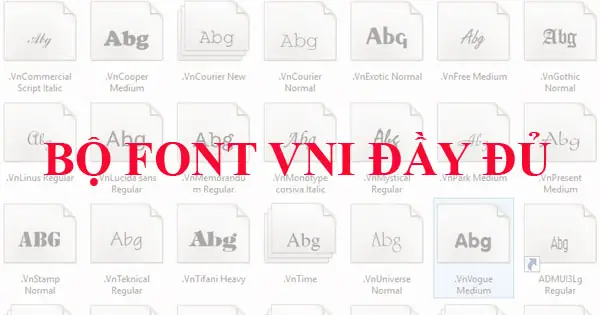
1. Tại Sao Bạn Cần Font Chữ VNI?
Font VNI là bộ font chữ tiếng Việt được phát triển bởi công ty Văn Lang, cung cấp các font hỗ trợ Unicode và TCVN3, giúp người dùng gõ tiếng Việt không dấu một cách chính xác. Các font VNI phổ biến như VNI-Times, VNI-Arial, VNI-Angie, VNI-Constantia, VNI-Cambria… đều được thiết kế đẹp, dễ đọc, phù hợp cho cả văn bản in ấn và trình chiếu.
Ưu điểm vượt trội của font VNI:
• Hỗ trợ đầy đủ dấu thanh tiếng Việt.
5. Top 10 Font Chữ VNI Phổ Biến Nhất
Dưới đây là những font VNI được ưa chuộng nhất, phù hợp cho từng mục đích sử dụng:
Font Đặc Điểm Ứng Dụng Phù Hợp
VNI-Times Giống Times New Roman, dễ đọc Văn bản hành chính, học tập
VNI-Arial Sans-serif, hiện đại Slide PowerPoint, bảng biểu
VNI-Angie Phong cách, mềm mại Thiết kế poster, ấn phẩm
VNI-Constantia Chữ dày, sang trọng Báo cáo, luận văn
VNI-Cambria Cân đối, đẹp mắt Tài liệu học thuật
VNI-Garamond Chữ in đậm, cổ điển Ảnh in, thiệp mời
VNI-Helvetica Phẳng, hiện đại Logo, banner
VNI-Courier Giống chữ máy đánh Tài liệu kỹ thuật
VNI-Tahoma Nhỏ gọn, dễ nhìn Email, chat
VNI-Georgia Chữ nghiêng nhẹ, sang trọng Bìa sách, tạp chí
Lưu Ý: Mỗi font đều hỗ trợ cả UnicodeTCVN3, đảm bảo gõ tiếng Việt chính xác trên mọi ứng dụng.